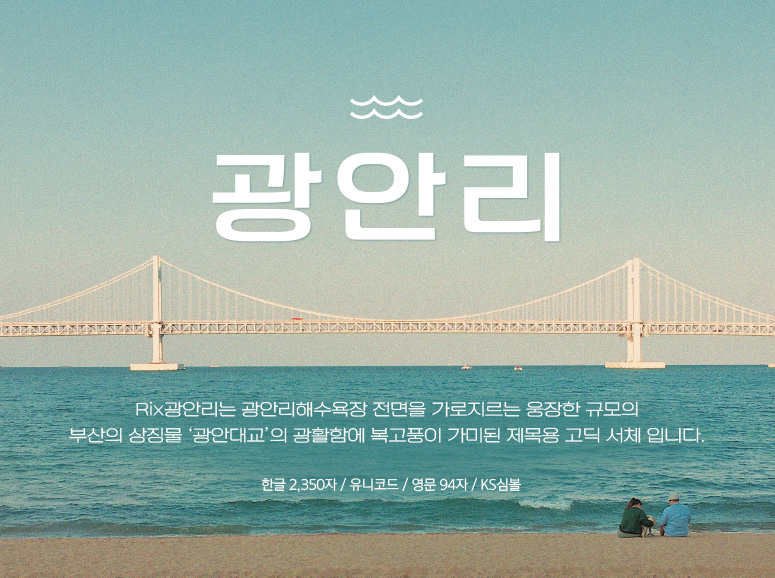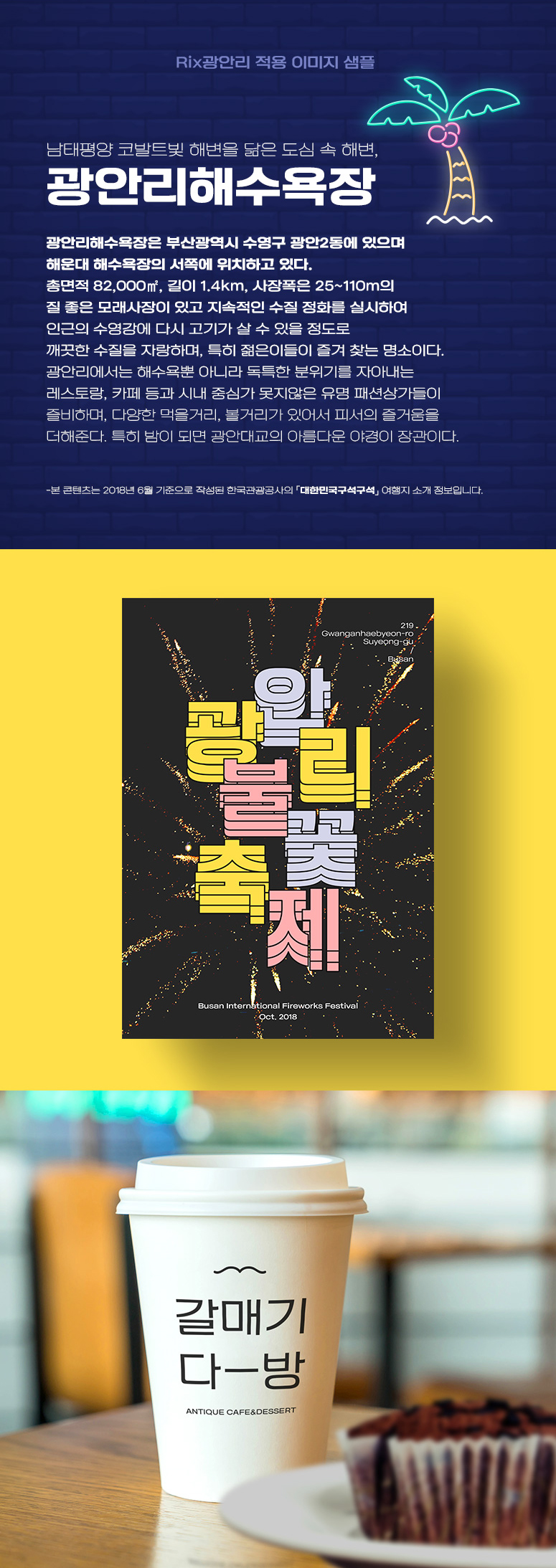
Rix광안리는 부산의 광안리해수욕장 전면을 가로지르는 웅장한 규모의 상징물 '광안대교'를 컨셉으로 광활함과 복고풍이 가미된 제목용 폰트입니다. 잔잔한 해변처럼 평평한 글자의 스타일과 수평선처럼 쭉 뻗어 나가는 형태의 '이응'꼴, 시원하게 불어오는 바람과 같은 부드러운 곡선은 광안리 특유의 넓고 광활한 느낌을 표현 하였습니다.